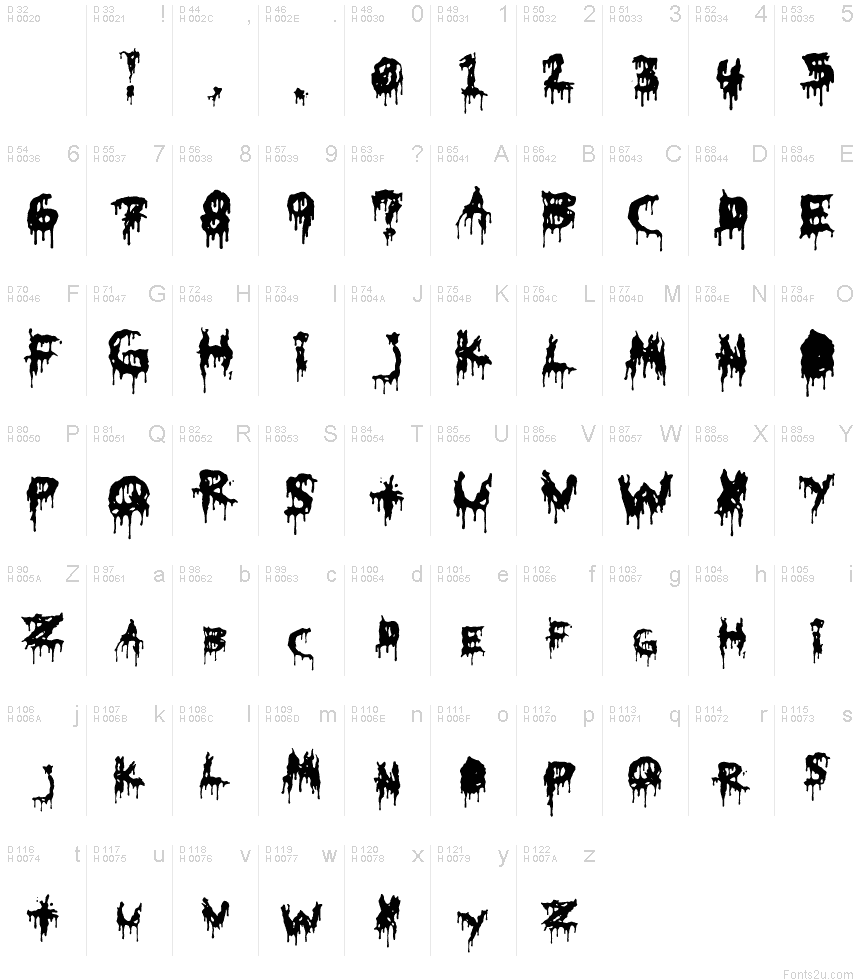
HoMicIDE EFfeCt od Nihilschiz Fonts to darmowy, przerażający krój pisma typu display, który wygląda jak litery wykute w gęstym, ściekającym tuszu. Każdy znak opada i wyciąga się w dół w lepkich smugach, jakby wciąż był mokry, nadając nagłówkom visceralny, krwawy charakter. Nierówne sylwetki i zbite, gęste kształty budują natychmiastowe napięcie, dzięki czemu nawet jedno słowo może wyglądać jak plakat filmowy.
Używając HoMicIDE EFfeCt, przeniesiesz swoje ulotki na Halloween, szyldy do nawiedzonych domów, tytuły slasherów, branding escape roomów czy menu gier grozy na poziom kultowy. Ten darmowy font świetnie sprawdzi się również w logotypach metalowych zespołów czy na mrocznych okładkach książek, jeśli użyjesz go w dużym rozmiarze i pogrubieniu. Dla zachowania czytelności, w tekstach głównych połącz go z czystym krojem bezszeryfowym, a HoMicIDE EFfeCt zarezerwuj dla najbardziej wyrazistych, mrożących krew w żyłach haseł.